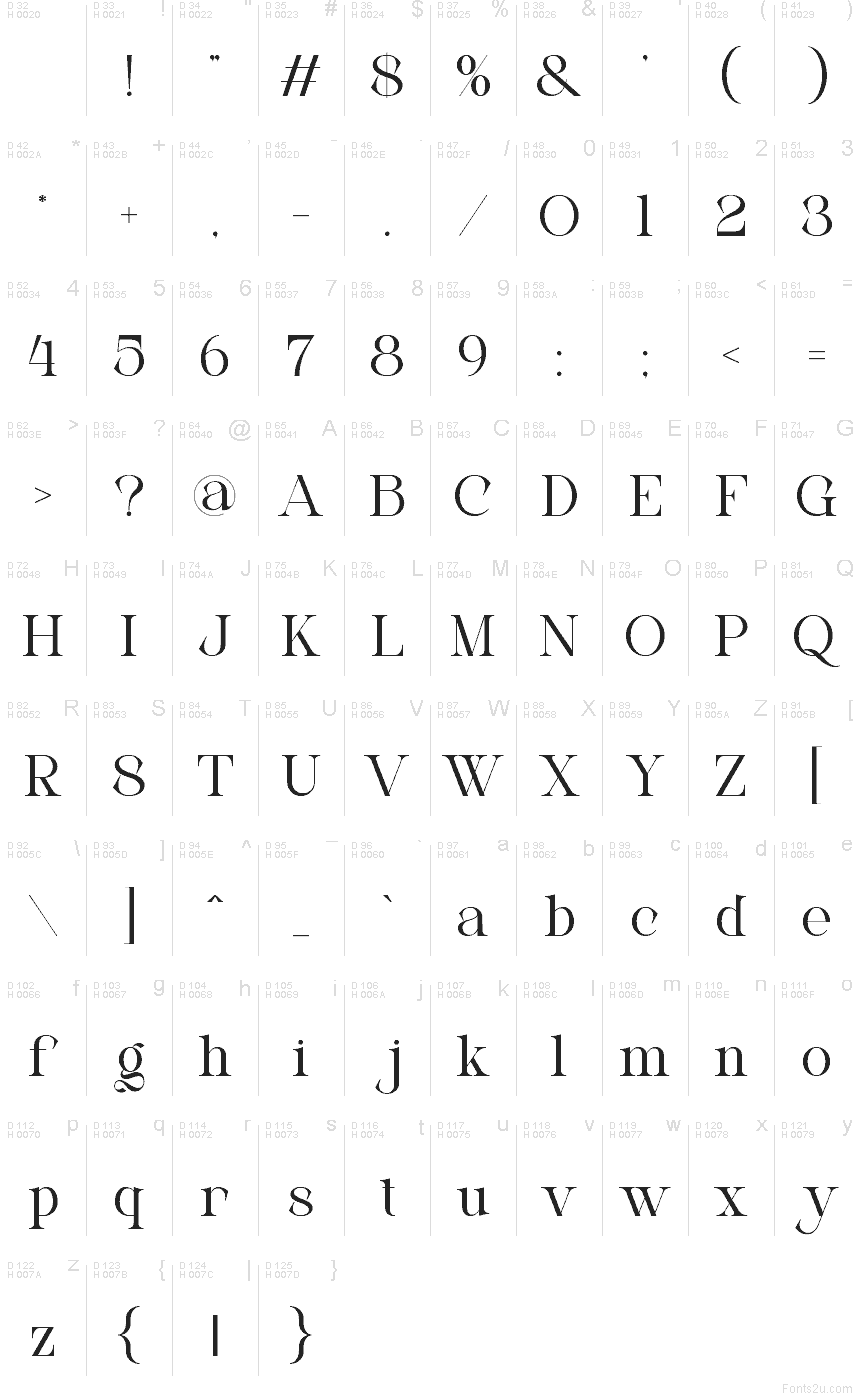
Glovar
Glovar di Ermedia Studio è un carattere con grazie gratuito e ad alto contrasto, contraddistinto da proporzioni maestose ispirate alla moda. Ampi tratti verticali incontrano dettagli sottilissimi e grazie nitide, mentre le curve generose donano alle lettere una silhouette elegante ma dal tocco teatrale.
Le testate di riviste sono il suo contesto ideale, in particolare nell'editoria di moda, cultura o lusso. Si adatta molto bene anche a confezioni di profumi e manifesti per eventi. Le sue linee sinuose possono richiamare i panneggi dei tessuti o la fotografia di prodotto, rendendo il testo parte integrante del tema visivo anziché una didascalia neutra.